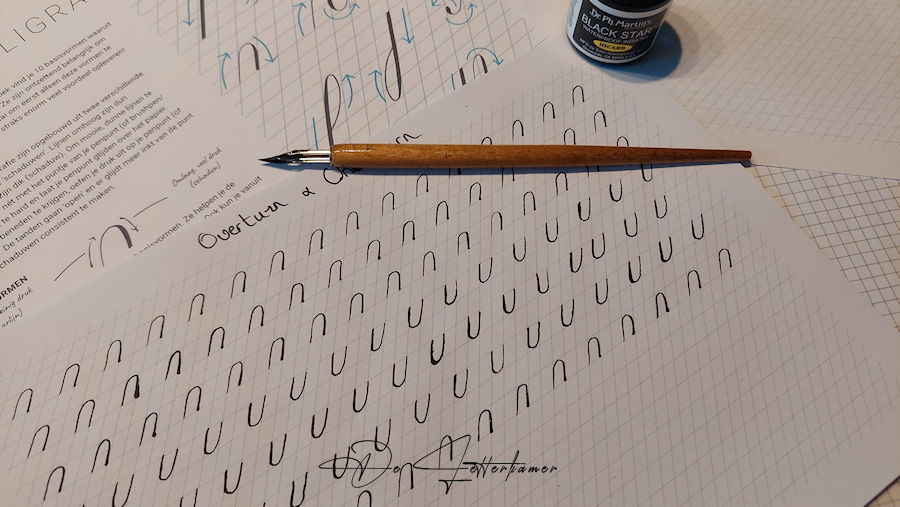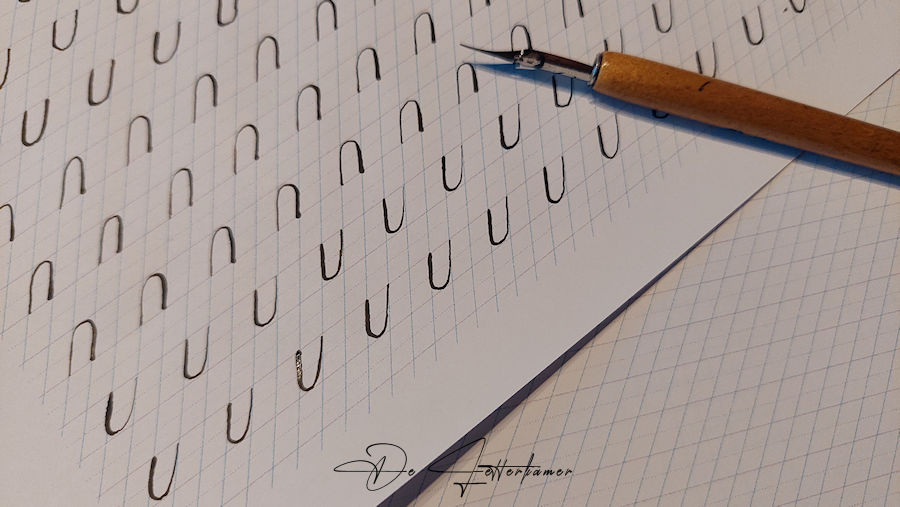
De dag was weer vlug voorbij, de avondzon gluurt door mijn raam heen, tijd om even wat te oefenen. Ik neem mijn materiaal, leg alles op mijn houten tafel, het is mijn gewone tafel in de woonkamer, deze wordt gebruikt om te ontbijten, onze maaltijd te verorberen en dus ook voor het hobby. Een allround tafel, een geleefde tafel.
We gaan beginnen met de volgende 2 basisvormen: de overturn en de underturn. Dit is dus met een boog. De overturn is met het boogje bovenaan, de underturn met het boogje onderaan.
Het ging niet meteen deze avond, er leek iets mis te zijn met de nib. Ik had precies telkens dikkere lijnen, heel onregelmatig.
Ik had ze nochtans schoon gemaakt de dag ervoor, maar het bleek toch niet voldoende te zijn. De nib heb ik weer verwijderd en met een oorstokje, lauw water en wat dreft proper gemaakt.
En opnieuw begonnen op hetzelfde blad, en ja hoor, het ging al veel beter. Ik was dus juist. Je ziet het goed, nog steeds met de rechte pen.
De laatste paar lijnen gingen al veel beter.
Ik heb bij Rosanne, eens naar haar video’s gekeken, hoe exact ze juist die lijnen trekt. Die dikkere lijnen beginnen en stoppen ergens net voor een bocht. Daar was ik dus verkeerd in. Dus terug opnieuw. Je moet op zoveel details letten.
En het zit ook meestal in de details. Ondertussen heb ik ook een oefenboek besteld “Copperplate Calligraphy Practice Book”, eens benieuwd of ik ook hieruit kan van leren.
Of ik het leuk vind? Ja, echt wel, de rust die je krijgt door het geluid van de pen, en het volgen van de pen, de inkt die mooi vloeit over het papier.